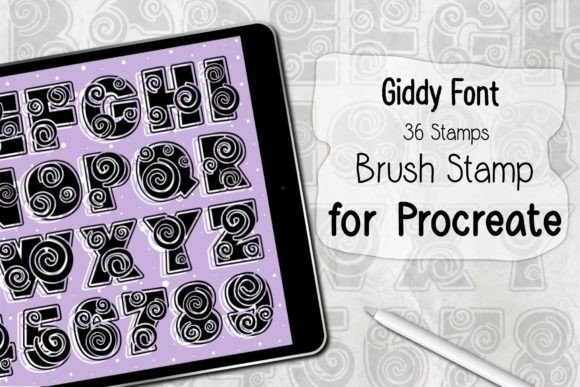
Giddy Font Procreate Brush Stamp
Mencari elemen reka bentuk yang sesuai boleh menjadi mencabar, tetapi Giddy Font Procreate Brush Stamp menawarkan koleksi luar biasa yang menaik taraf karya anda serta-merta.
Dicipta dengan ketepatan, Giddy Font Procreate Brush Stamp menyediakan vektor yang bersih, tipografi yang licin dan lesen komersial untuk ketenangan fikiran.
Sama ada anda mencipta produk POD (Print on Demand), jemputan perkahwinan atau grafik media sosial, Giddy Font Procreate Brush Stamp amat bersesuaian.